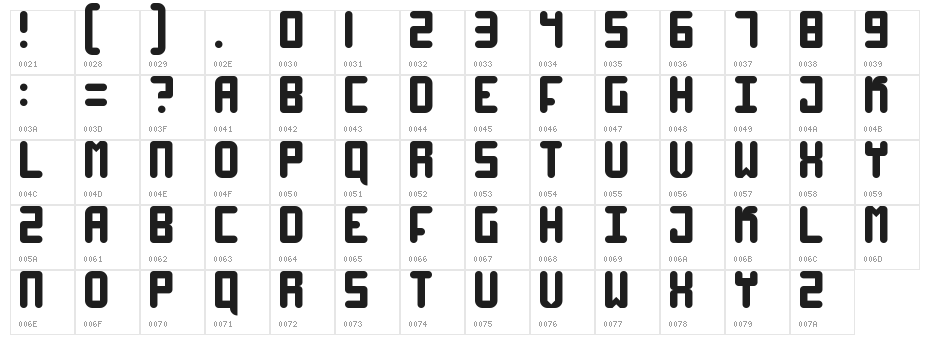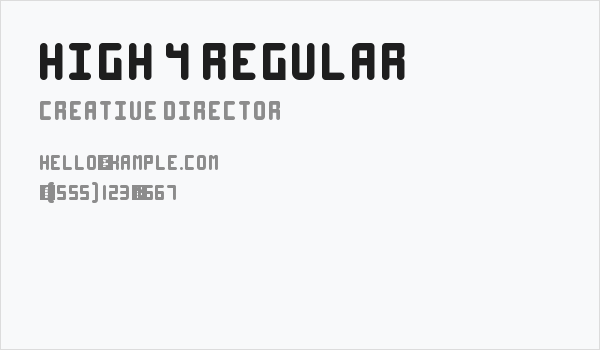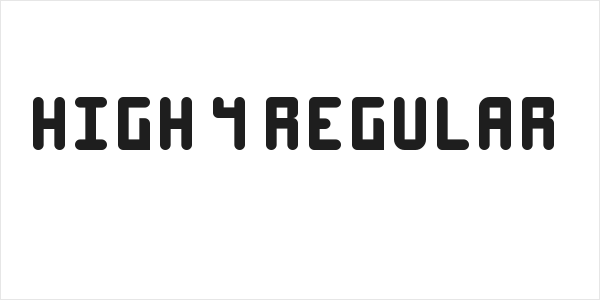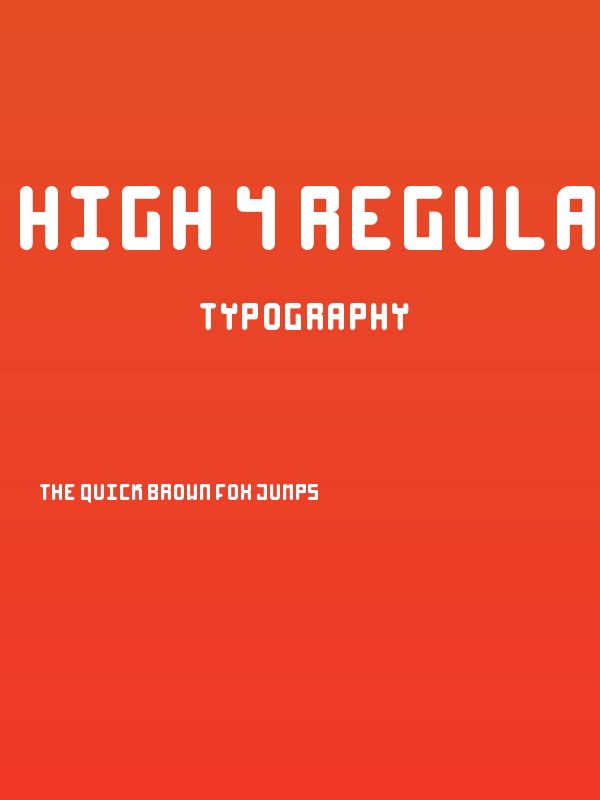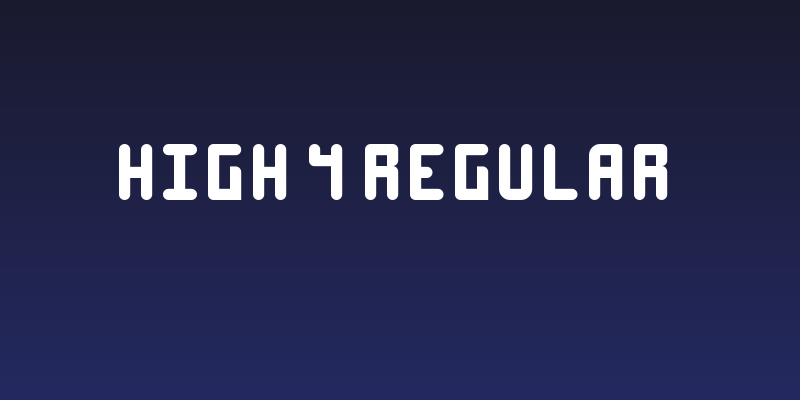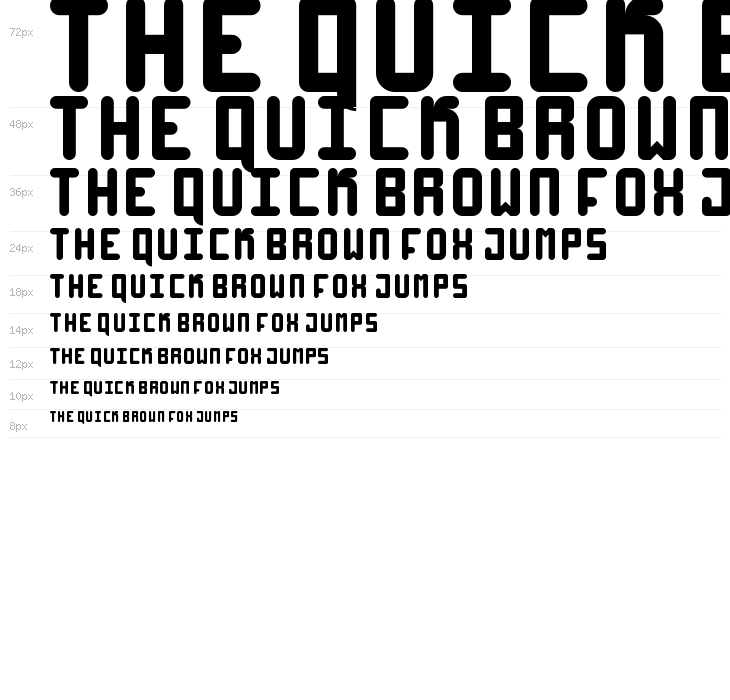
High 4 Regular Font
| Категория | Thick |
| Область применения | Headlines, Logos, Signage |
| Рекомендуемые проекты | Ideal for branding, signage, posters, and digital interfaces where a modern and friendly look is desired. |